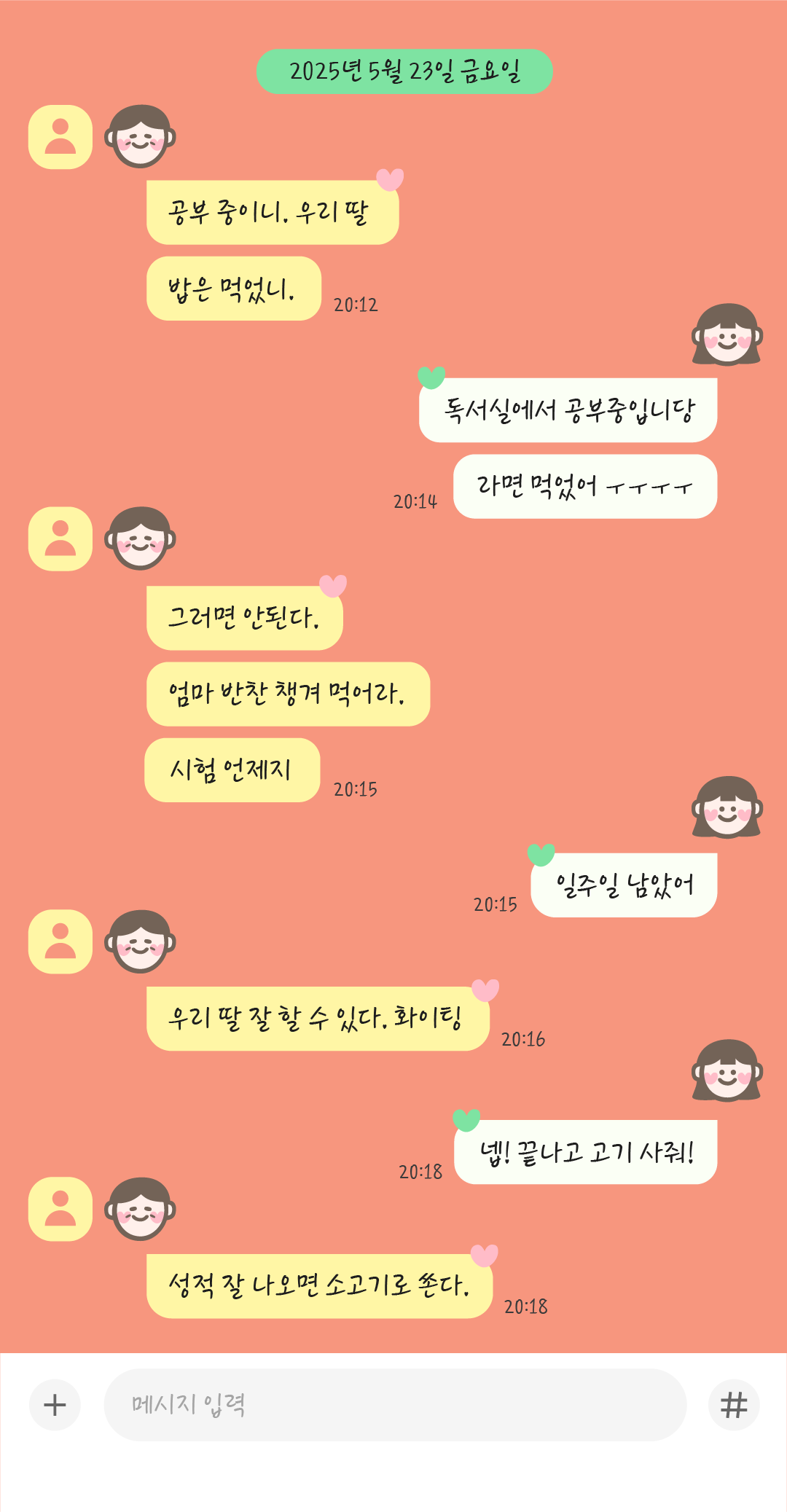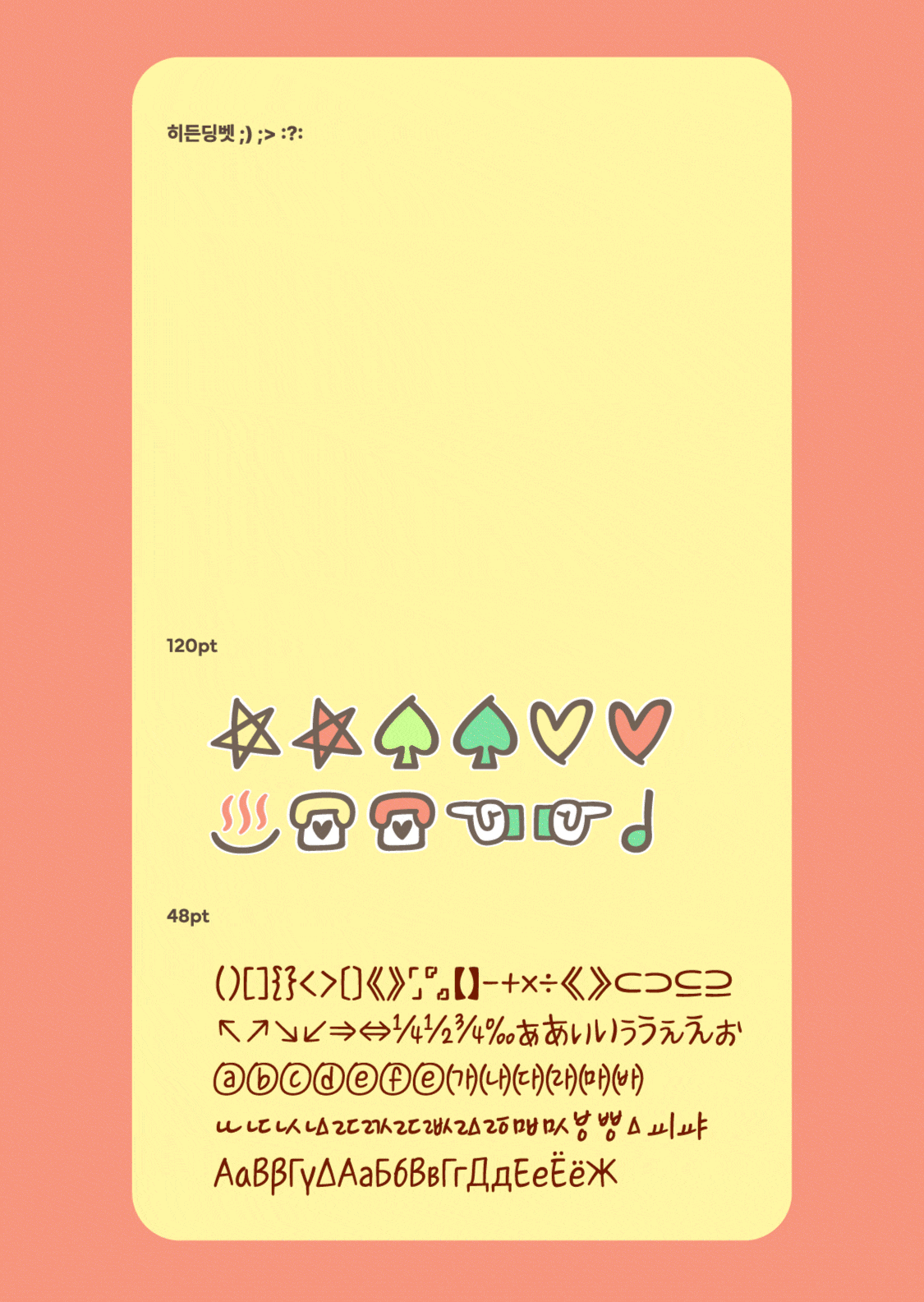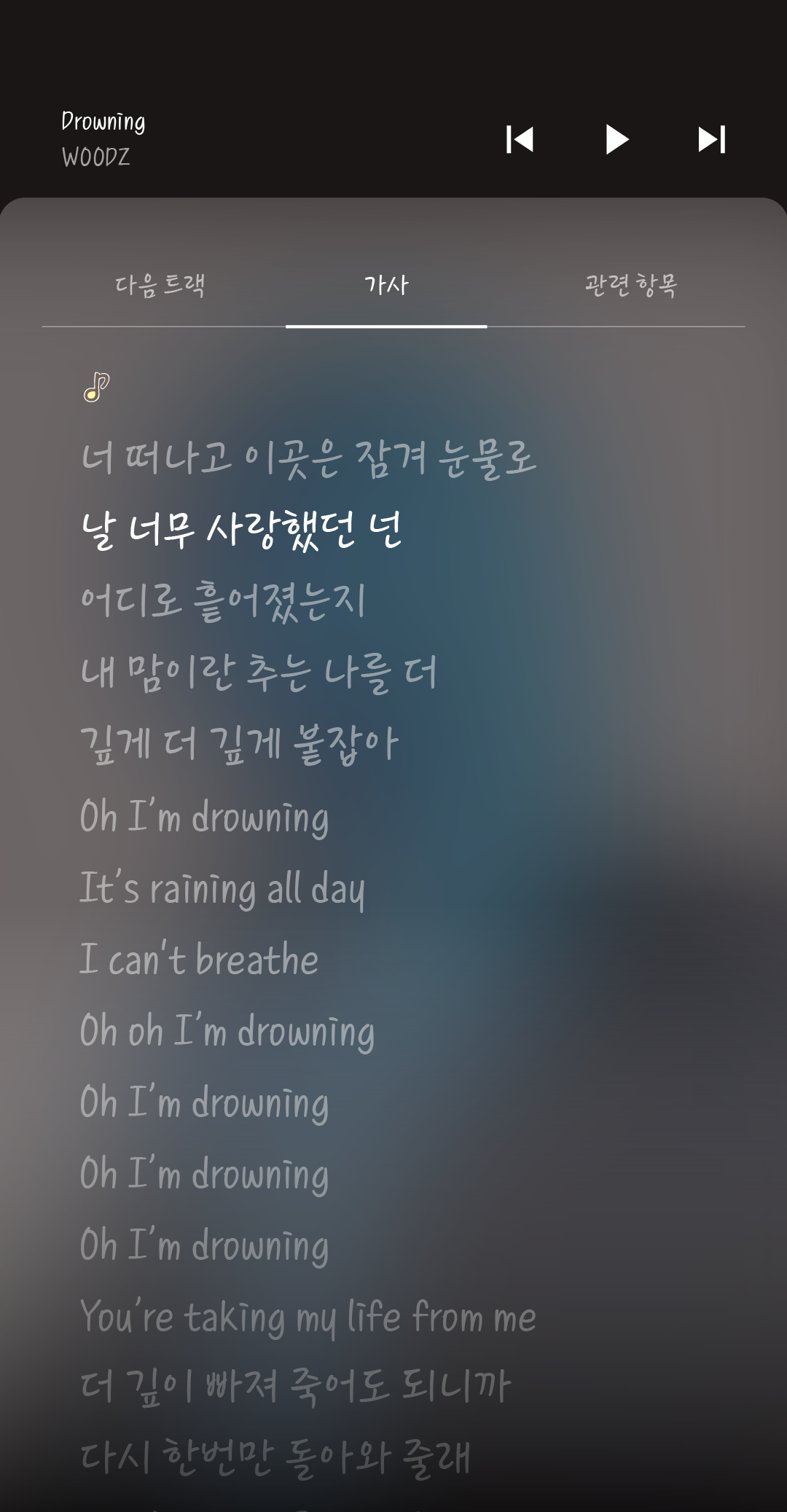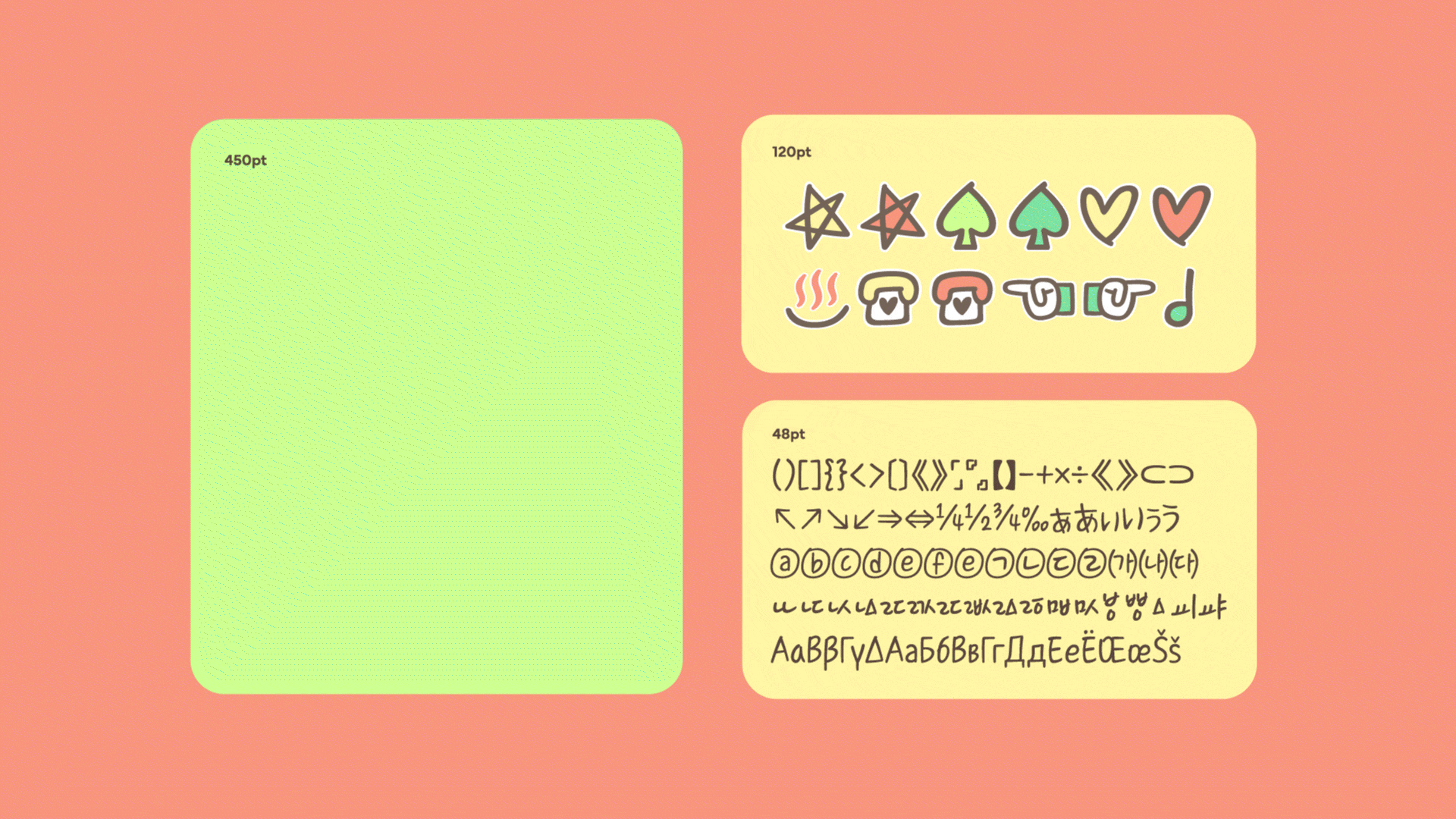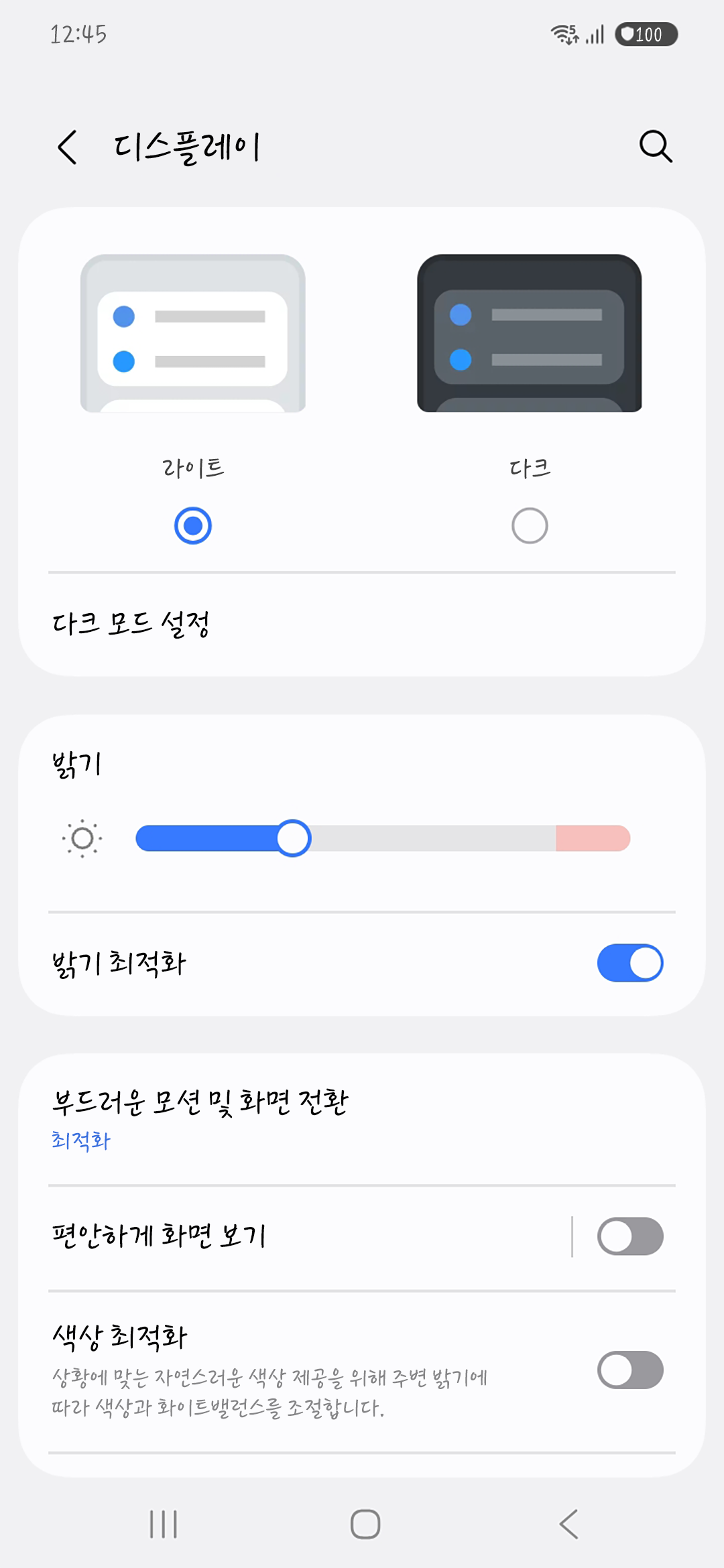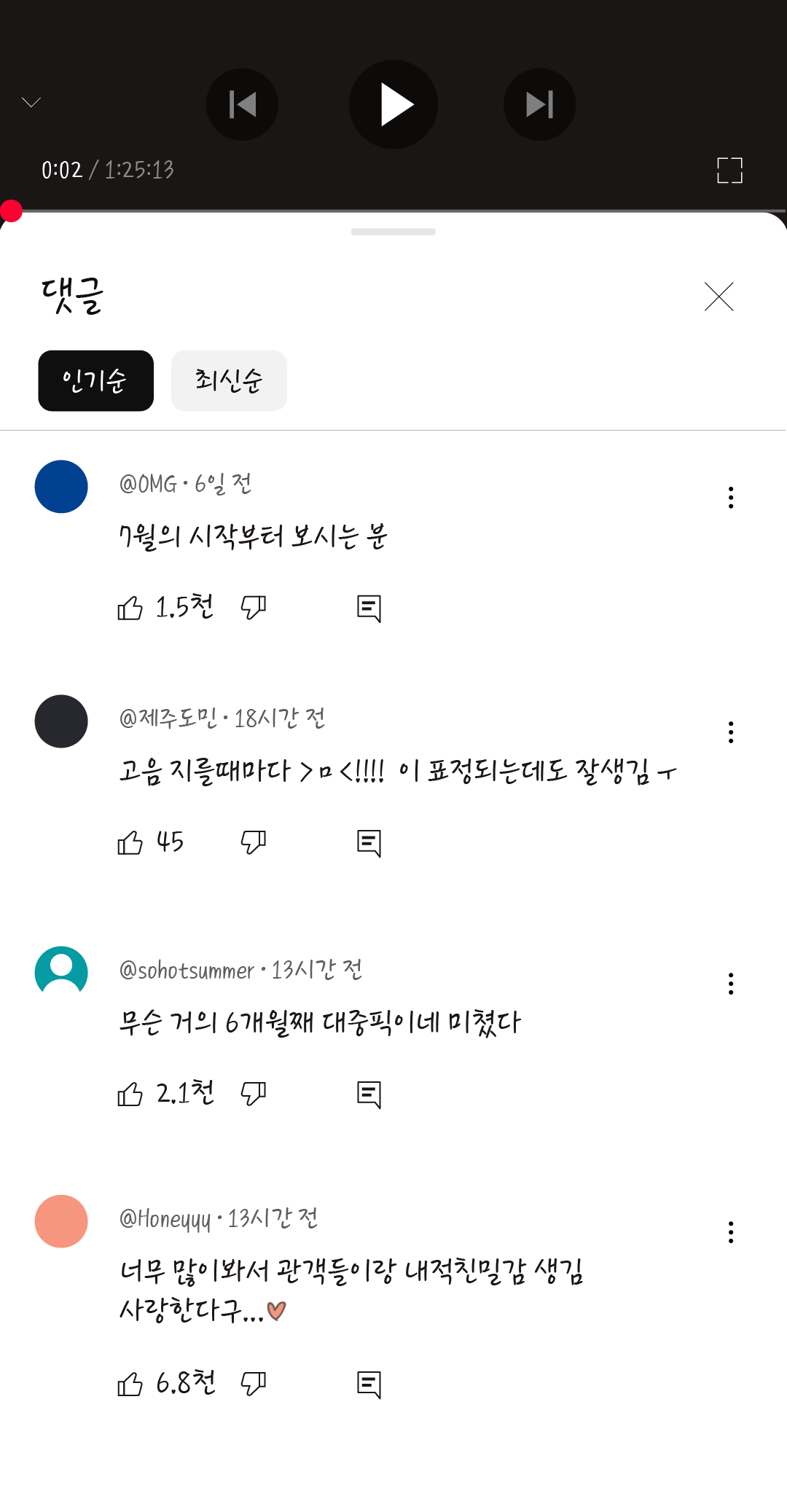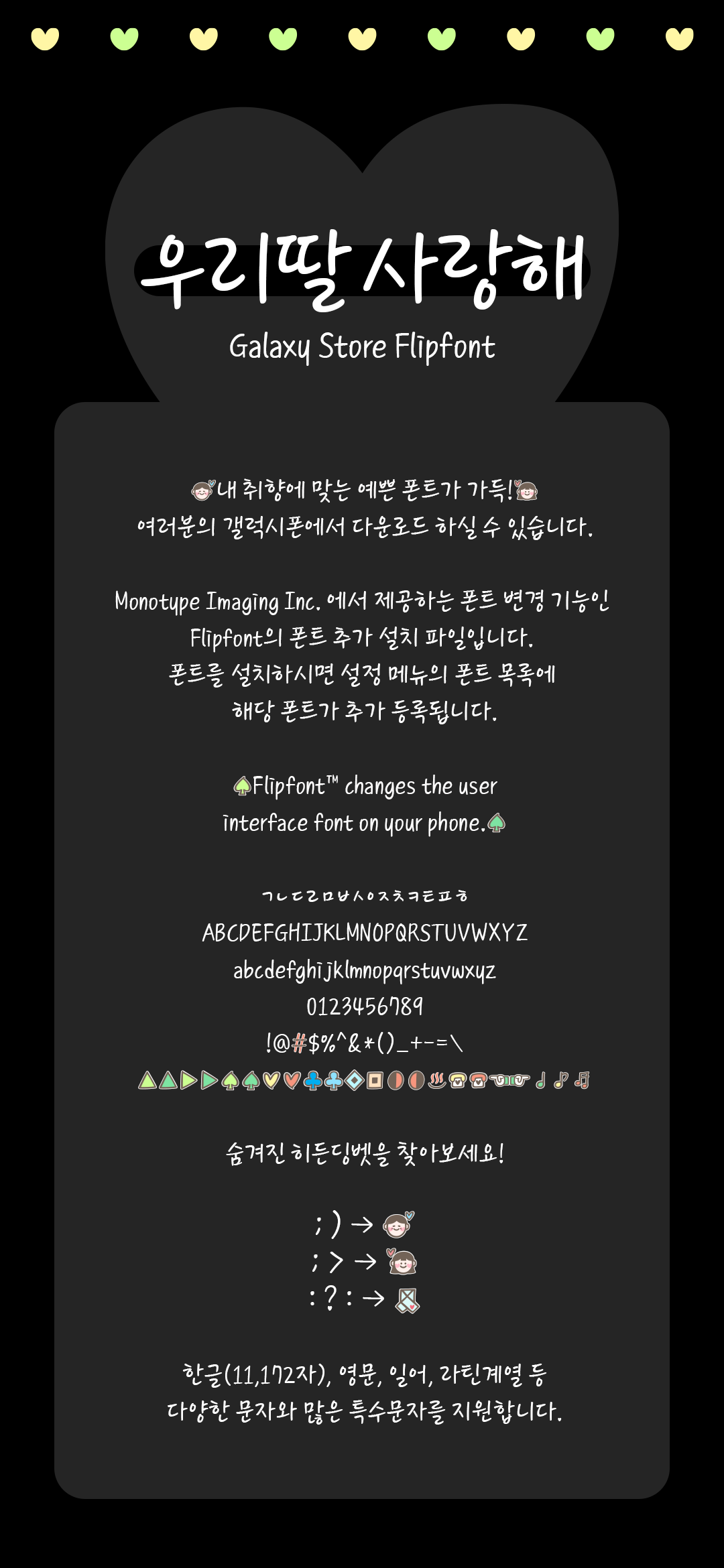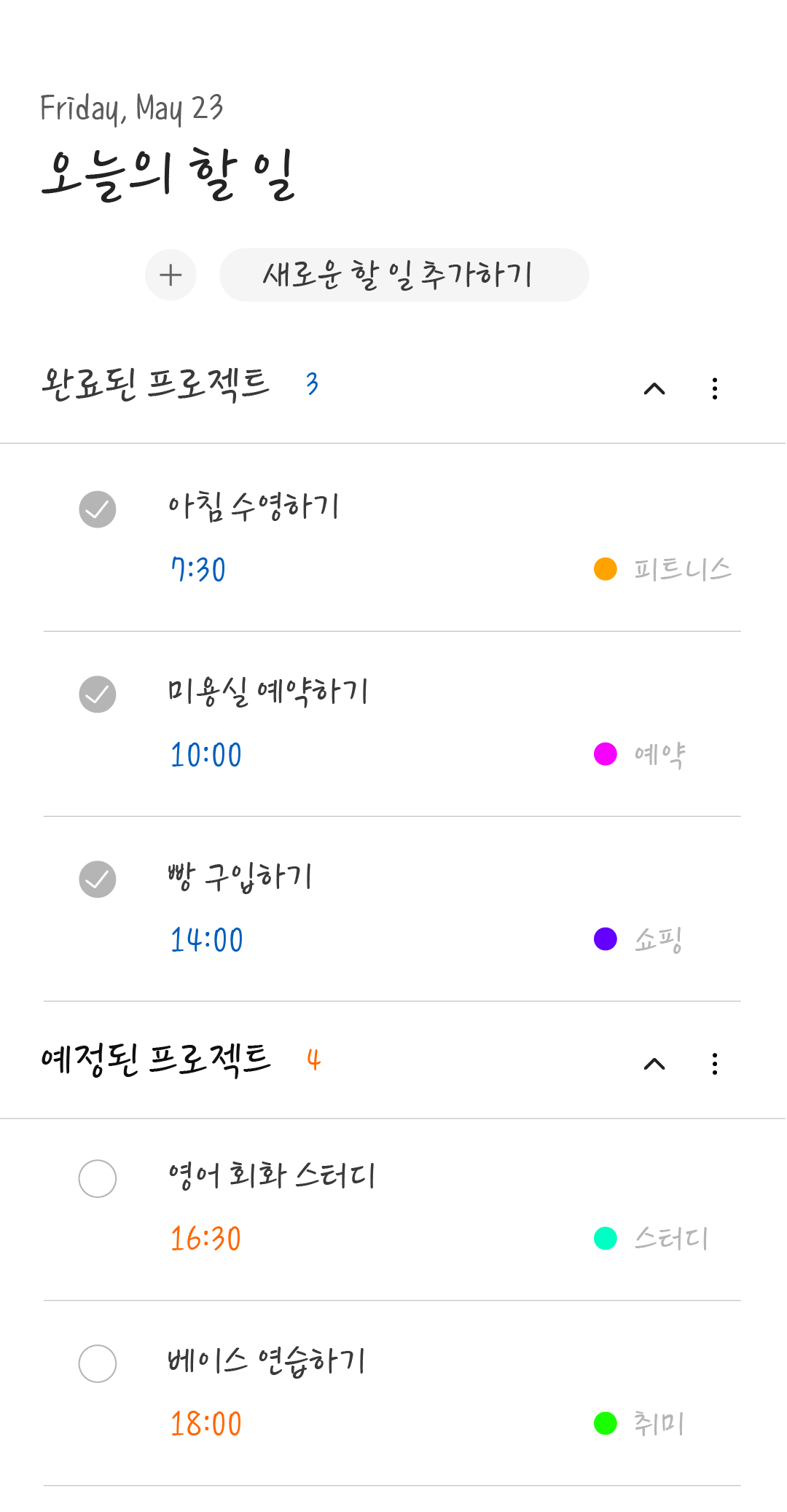
이 서체는 자연스럽게 써내려간 손글씨를 바탕으로, 사랑하는 마음이 전해지도록 친근한 느낌으로 작업된 서체입니다. 정갈하고 단정하면서도 필력이 느껴지며, 부드러운 이미지도 가진 서체입니다.
이 서체는 자연스럽게 써내려간 손글씨를 바탕으로, 사랑하는 마음이 전해지도록 친근한 느낌으로 작업된 서체입니다.
정갈하고 단정하면서도 필력이 느껴지며, 부드러운 이미지도 가진 서체입니다.
서체 이름
TE 우리딸사랑해